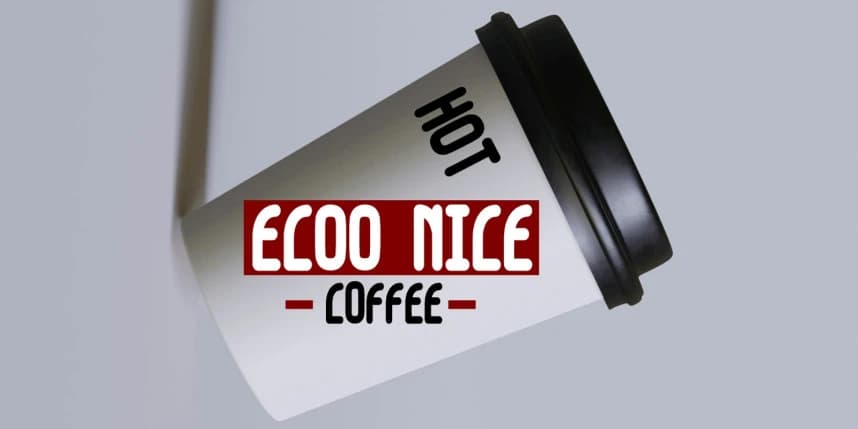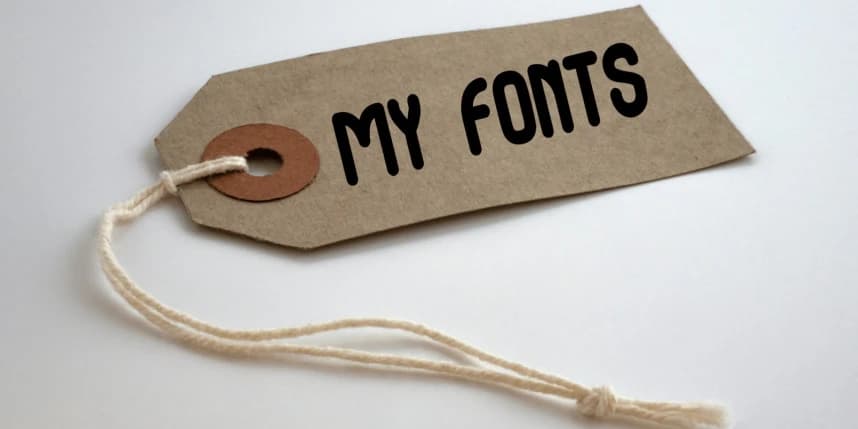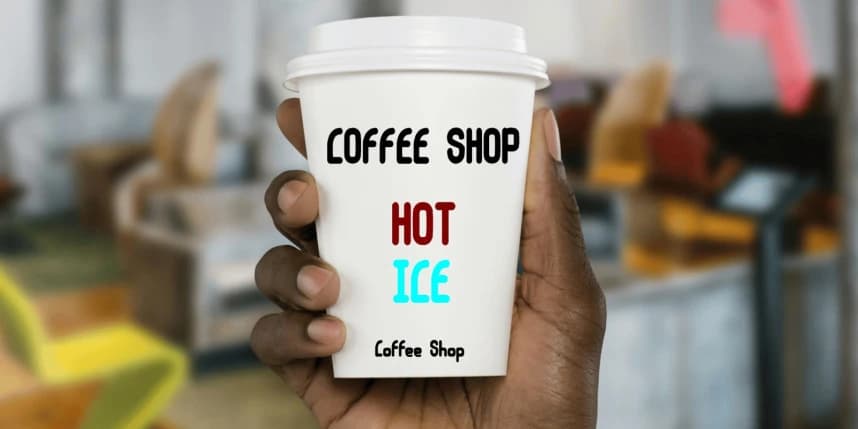
Algojo Yazı Tipi
ALGOJO Font, cesur, kendinden emin ve temiz bir estetiğe sahip olan modern bir gösterim sans-serif yazı tipidir. Güçlü harf biçimlerini minimalist bir dokunuşla sergileyen ALGOJO, herhangi bir görsel kompozisyonda zahmetsizce öne çıkar ve dikkat çeker.
ALGOJO Font, cesur, kendinden emin ve temiz bir estetiğe sahip modern bir gösteri sans-serif yazı tipidir. Minimalist bir dokunuşa sahip güçlü harf biçimleriyle ALGOJO, herhangi bir görsel komposizisyonda zahmetsizce öne çıkar ve dikkat çeker.